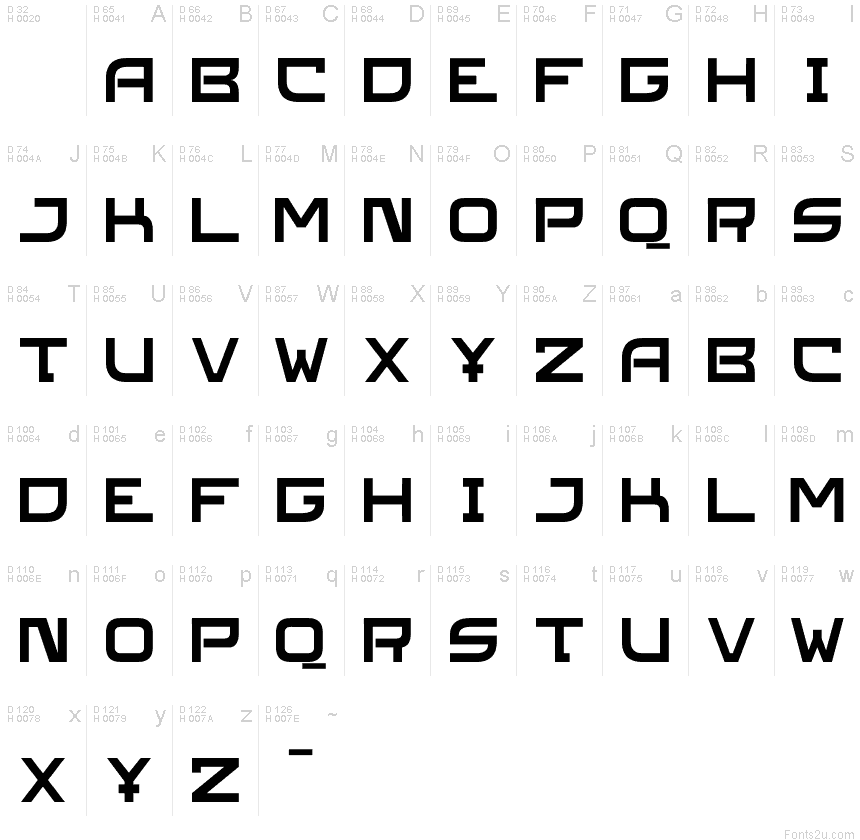
SL Panzerkardinal, bezplatné techno display písmo od Luise Huacuja Garcii, přichází s tvrdým sci-fi postojem postaveným na čtvercových tvarech a hluboce zaoblených rozích. Velká písmena působí široce, oříznutě a pevně pod kontrolou; tahy do sebe zapadají ve strojově vyřezávaném rytmu, který je futuristický, aniž by působil rušivě.
Hodí se na plakáty, herní loga, obaly alb, titulky a obalový design, kde bezplatné písmo vyžaduje kompaktní, filmový říz. Protože písmena v sobě nesou tolik atmosféry, funguje skvěle i pro krátké nadpisy a monogramy, zejména pokud hledáte uzavřený, industriální vzhled namísto něčeho hravého či retro.